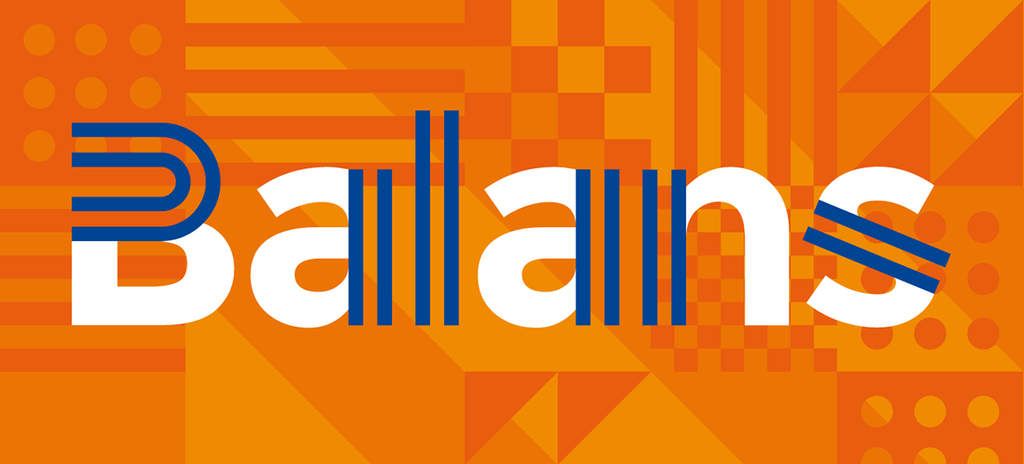
A Balans Font Family é uma elegante família de fontes criada pelo designer Hamilton, inspirada no conceito holístico de “balance”. Na sua criação, a família busca equilibrar formas geométricas básicas com citações de personalidades que o próprio Hamilton considera mentores e inspirações. Após viver uma experiência crítica, passou por um prolongado período em tratamento médico fora do Brasil, voltando para casa reconstruído em todos os sentidos. Na recuperação, Hamilton percorreu um caminho de reflexão sobre a sua vida profissional como designer. Ele percebeu que buscava equilíbrio entre as formas e os significados das palavras. A inspiração nessa busca pelo equilíbrio é o mote para criar uma família de fontes única, onde formas geométricas básicas são adaptadas com citações de mentores pessoais, criando um diálogo visual entre a simplicidade e a profundidade emocional.